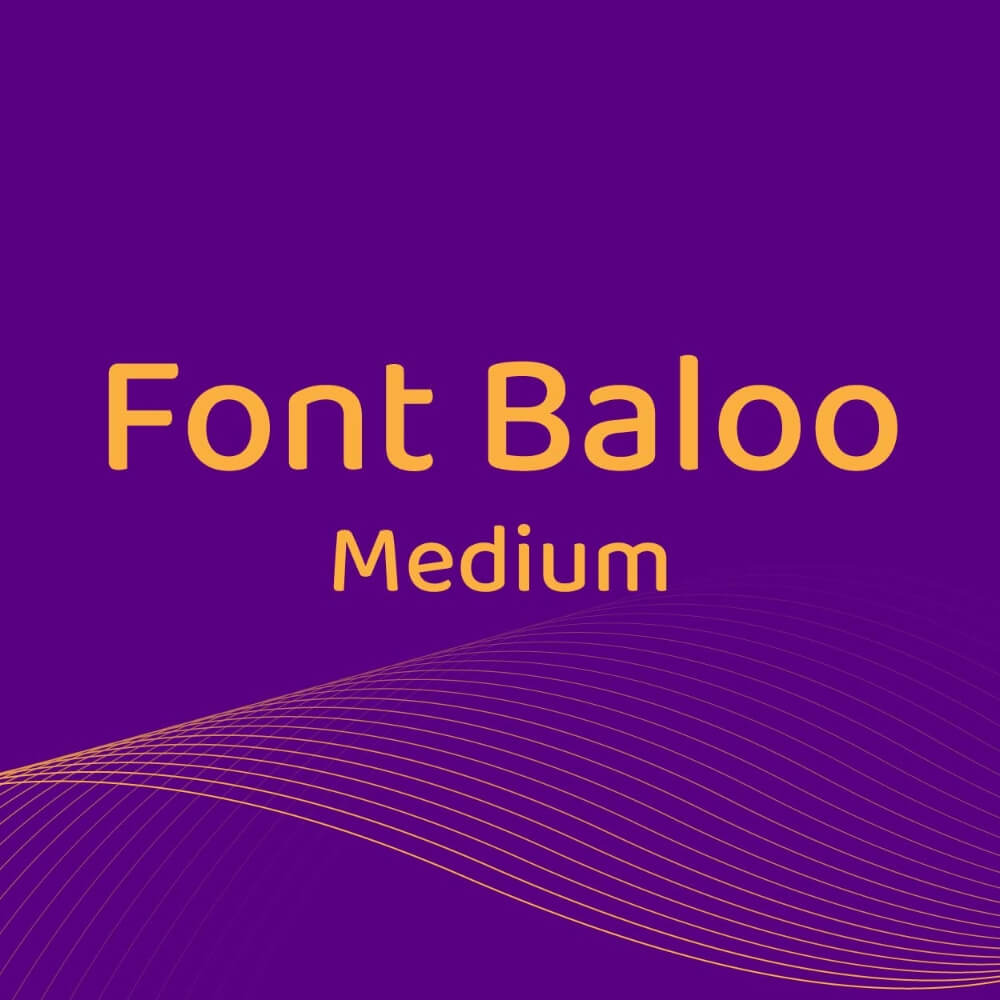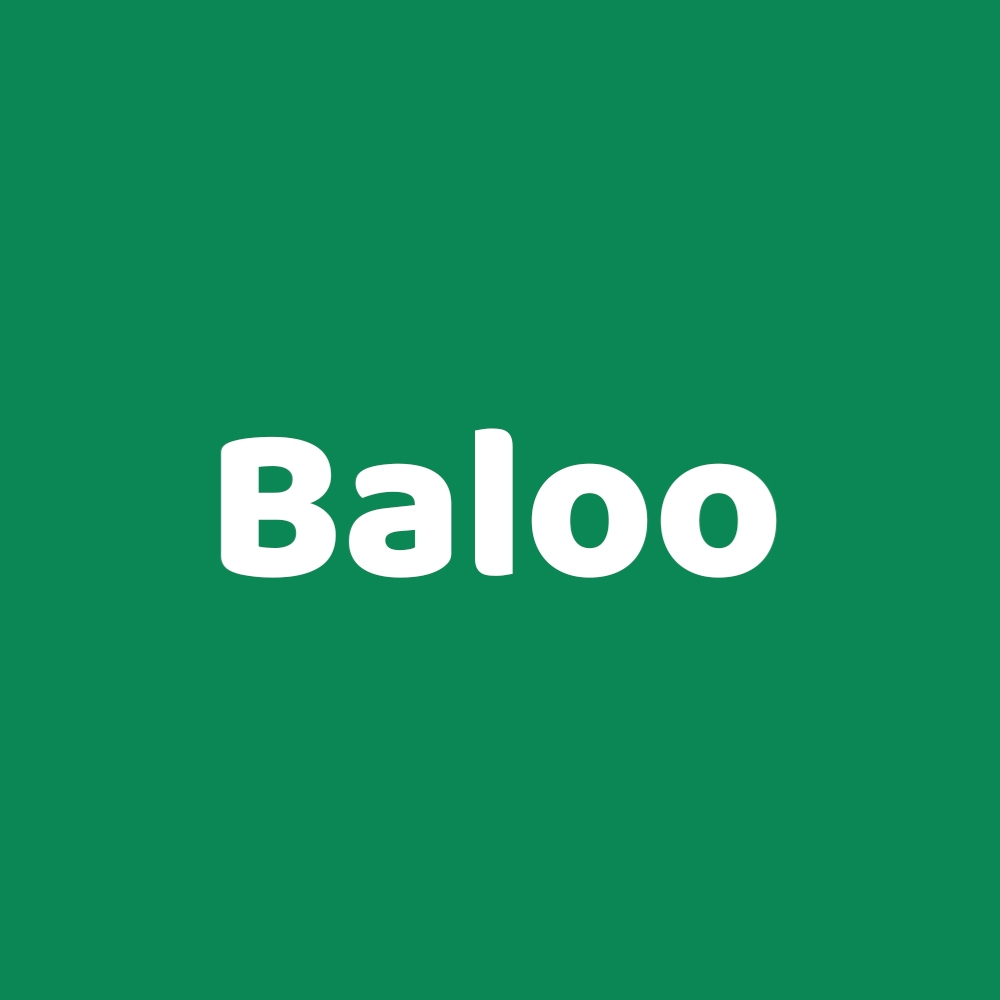
Baloo font việt hóa là font chữ tròn trịa, dễ thương, vui nhộn được thiết kế đặc biệt cho sản phẩm và nội dung dành cho trẻ em. Font chữ này được sử dụng rộng rãi trong thiết kế logo trường mầm non, sách thiếu nhi, bao bì đồ chơi và ứng dụng học tập nhờ nét chữ an toàn, thân thiện với trẻ nhỏ.
- Baloo Regular: Phiên bản tiêu chuẩn với độ đậm vừa phải.
- Baloo Extra Bold: Cực kỳ nổi bật, phù hợp cho biển hiệu và tiêu đề lớn.
- Baloo 2 font việt hoá (Variable): Phiên bản mới nhất với 5 mức độ đậm nhạt khác nhau, cực kỳ linh hoạt cho dàn trang.
Tại sao font chữ baloo việt hóa lại được ưa chuộng trên bao bì?
Không phải ngẫu nhiên mà font chữ baloo việt hóa xuất hiện dày đặc trên các kệ hàng siêu thị. Đặc trưng lớn nhất của nó là các đường cong không có góc cạnh sắc nhọn, tạo cảm giác an toàn, dễ gần và đầy sức sống.
Trong tâm lý học màu sắc và hình khối, các khối tròn giúp người tiêu dùng cảm thấy thư giãn và thiện cảm hơn. Vì vậy, khi in ấn bao bì bánh kẹo hay tem nhãn nước uống, Baloo giúp thương hiệu trông “ngon mắt” và dễ tiếp cận hơn so với các font chữ vuông vức.
Ứng dụng Baloo font việt hóa trong sản xuất quà tặng tại In Viva
Tại xưởng sản xuất của chúng tôi, baloo font việt hóa được ứng dụng vô cùng đa dạng nhờ tính chất “dễ in, dễ đẹp” của nó.
- In trên bình nước nhựa sinh học: Các nét tròn của Baloo cực kỳ phù hợp với kỹ thuật in lụa, giúp mực bám đều và không bị đứt nét ở các khúc cua của mặt trụ bình.
- Sản xuất túi vải canvas: Khi in nhiệt hoặc in lụa lên bề mặt vải có thớ to, Baloo với nét chữ mập mạp sẽ che đi được các khuyết điểm nhỏ của bề mặt vải, giúp nội dung luôn rõ ràng.
- Làm kỷ niệm chương mica: Các góc bo của font chữ Baloo khi chạy máy cắt laser trên mica tạo ra những đường cắt mượt mà, không gây sắc lẹm, đảm bảo an toàn khi sử dụng.
03 lỗi cần tránh khi in ấn bằng font chữ Baloo
Dù là một font chữ khá “lành tính”, nhưng khi tải font baloo việt hóa và sử dụng cho in ấn công nghiệp, bạn vẫn cần lưu ý một số điểm sau để sản phẩm đạt chất lượng cao nhất.
- Khoảng cách dòng (Leading): Do Baloo có các ký tự “bụng to”, nếu bạn để khoảng cách dòng quá hẹp, các dấu thanh của dòng dưới sẽ đè lên chân của dòng trên, gây rối mắt.
- Sử dụng quá nhiều chữ viết hoa: Font Baloo đẹp nhất khi viết thường (Lowercase). Nếu lạm dụng viết hoa toàn bộ (All caps), các khối tròn sẽ trở nên nặng nề và mất đi nét thanh thoát đặc trưng.
- Nhầm lẫn giữa các phiên bản: Một số bản tải lậu trên mạng bị lỗi bảng mã Unicode ở các ký tự như “ơ”, “ư”. Luôn kiểm tra kỹ trên file vector trước khi xuất phim in để tránh sai sót hàng loạt.
Lời khuyên: Khi in chữ Baloo màu sáng trên nền tối, hãy cẩn thận với hiện tượng “nuốt nét”. Bạn nên tăng khoảng cách giữa các chữ (tracking) thêm khoảng 20-50 đơn vị để chữ không bị dính vào nhau sau khi mực khô.
1. Baloo font có phù hợp để in logo trên áo đồng phục không?
Rất phù hợp. Baloo mang phong cách trẻ trung, năng động, cực kỳ bắt mắt khi in decal hoặc in lụa trên áo thun đồng phục của các câu lạc bộ hoặc quán cafe.